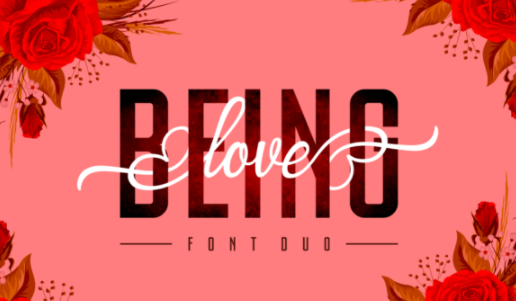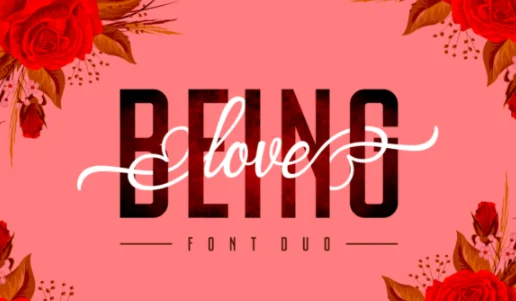
Название: Being Love Font (2022)
Being Love - это уникальный шрифтовой дуэт. Он включает в себя роскошный шрифт с разнообразными штрихами и яркую версию sans. Оба стиля прекрасно сочетаются друг с другом и обладают отличной читабельностью.
Используйте этот дуэт для создания уникальных дизайнов снова и снова!